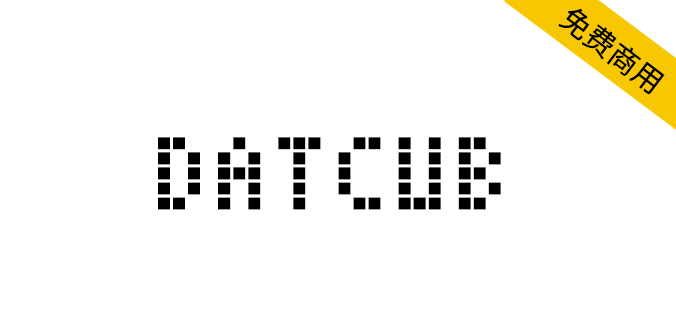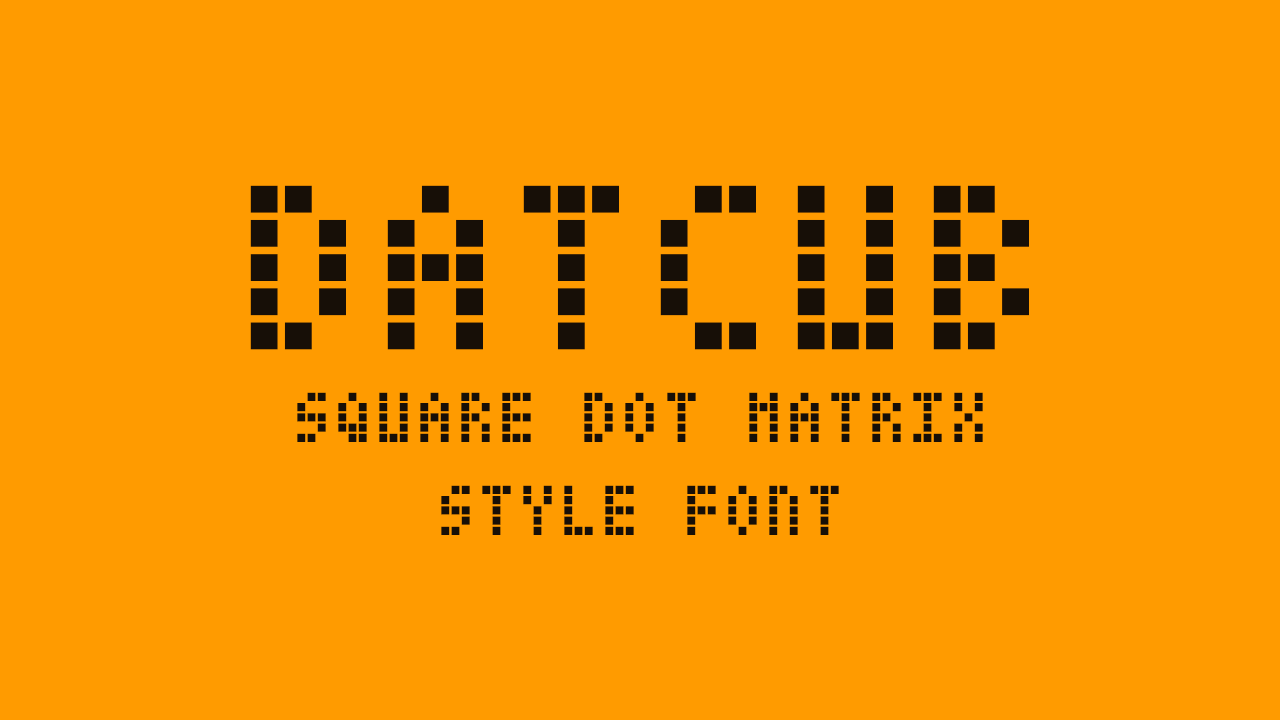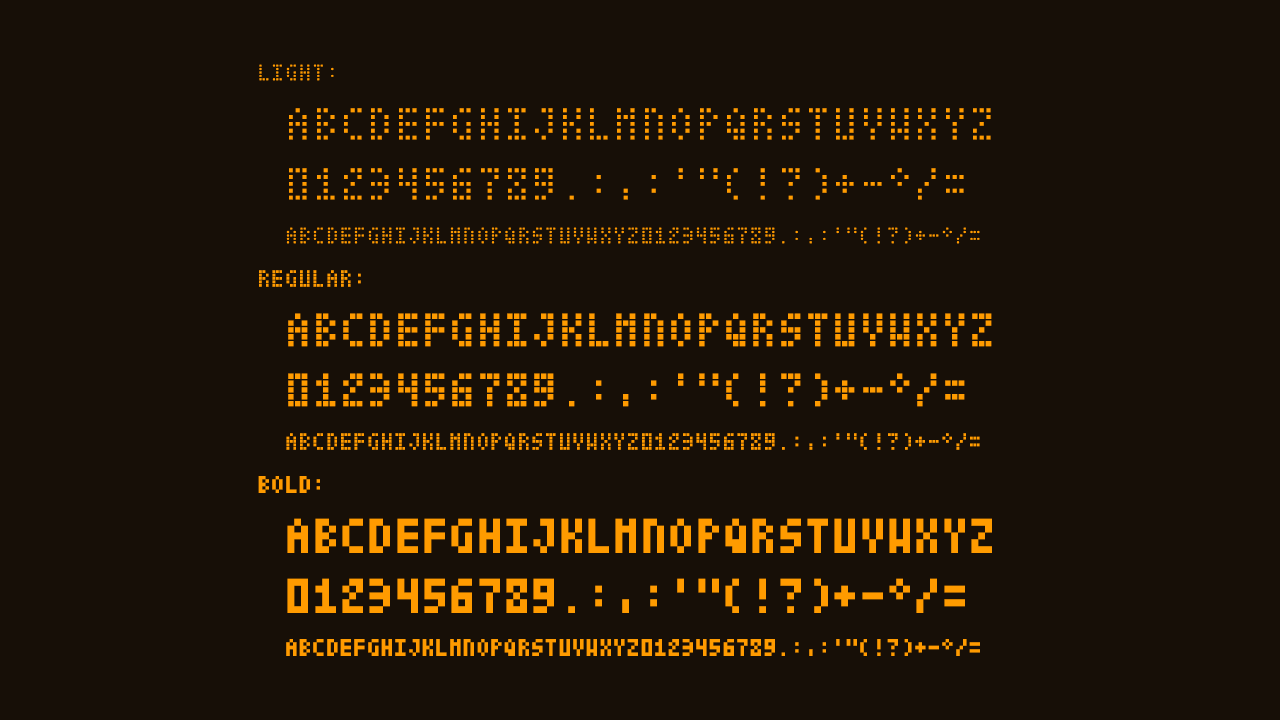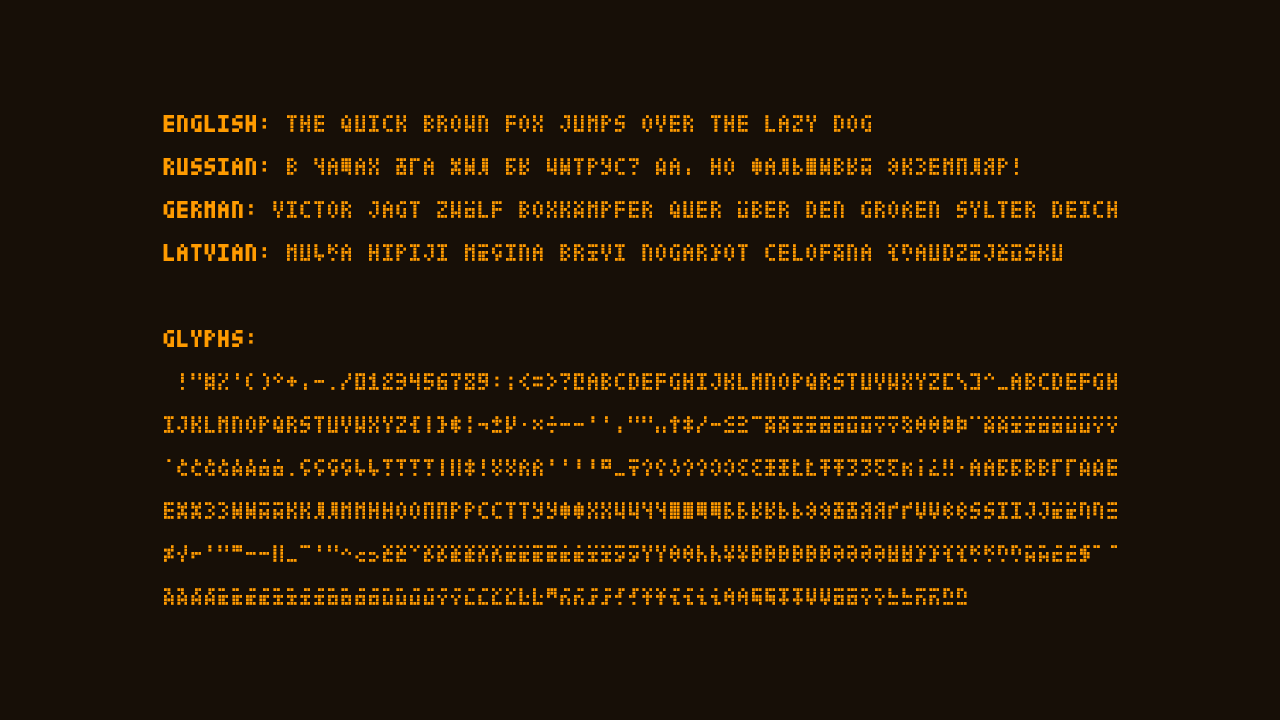
DatCub 是一款方形点阵样式免费英文字体,根据SIL OFL协议发布,包含 3 种样式(Regular、Bold、Light)和 410个字形。布局网格 3x5(固定宽度和高度)。
支持 33 种语言(Aja, 阿尔巴尼亚语, 白俄罗斯语, 保加利亚语, 加泰罗尼亚语, 克罗地亚语, 达格巴尼语, 荷兰语, 英语, 爱沙尼亚语, Fon, 德语, 印度尼西亚语, 意大利语, 拉丁语, 拉脱维亚语, 立陶宛语, 马赛语, Mapudungun, 蒙古语, 北萨米语, 波兰语, 俄语, 苏格兰盖尔语,塞尔维亚语、斯洛文尼亚语、西班牙语、他加禄语、特拉帕内克语、乌克兰语、乌兹别克语、西弗里斯兰语、祖鲁语。)